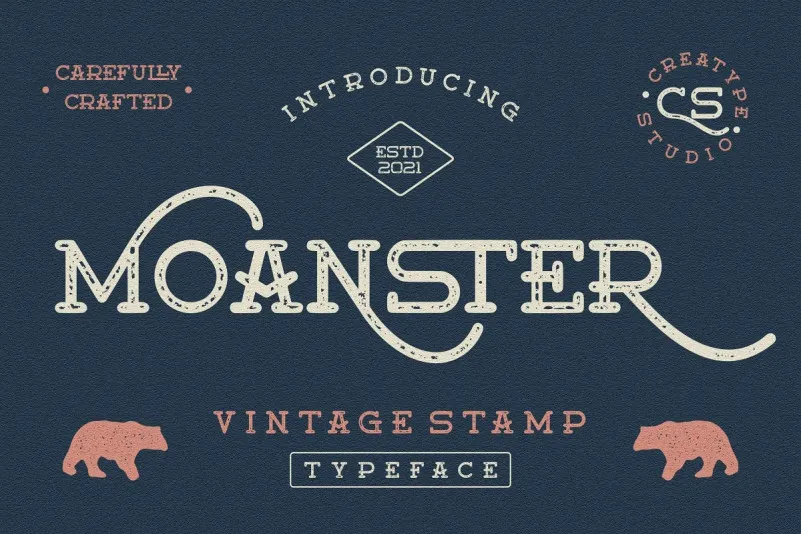
Moanster Display Font – Download Grátis
A Moanster Display Font nasceu do espírito inspirador de uma exibição vintage. Este estilo único oferece uma sensação aconchegante de antiguidade, com um toque clássico e artesanal feito à mão. Perfeito para projetos de marca, logotipos, designs de casamento, postagens no Facebook e Instagram, anúncios, embalagens de produtos, conceitos de produto, rótulos, fotografia, marcas e cartões de visita. Esta fonte atua como uma carta a mão digital, adequada para quaisquer projetos que requerem um toque autêntico do estilo humano. É perfeita para captar a atenção e destacar seu design nos mais variados formatos e ambientes, seja em campanhas de marketing ou em designs pessoais. Com o Moanster Display Font, você pode agregar vida e personalidade a qualquer projeto visual que possa precisar de uma sensação vintage e artesanal.